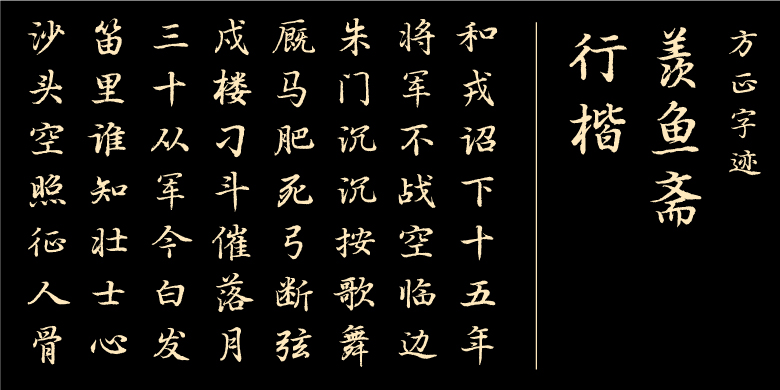
方正字迹-羡鱼斋行楷
方正字迹-羡鱼斋行楷,这款字体结构工整、笔画清晰,兼顾美观与易读性,适用于标题、正文、海报、包装、LOGO 等多种场景。字形优雅稳定,风格百搭耐看,适配日常排版与创意设计,让文字呈现更舒适、更具质感。方正字迹-羡鱼斋行楷一笔一画,皆是细节,以均衡的比例、流畅的线条打造舒适视觉体验,字形端正大气,风格简约现代。无论是商业设计、品牌宣传还是日常排版,都能轻松驾驭,让文字更有格调与力量。方正字迹-羡鱼斋行楷字体下载。
“羡鱼斋行楷”以传统帖学为基础,兼顾作为字库所必需的规范、实用、美观,努力做到雅俗共赏。